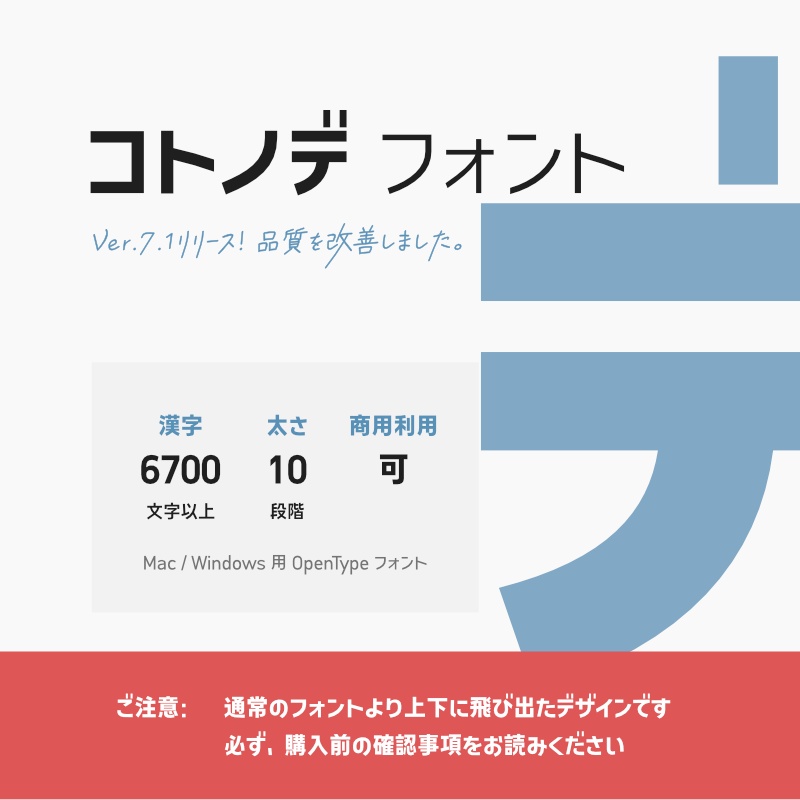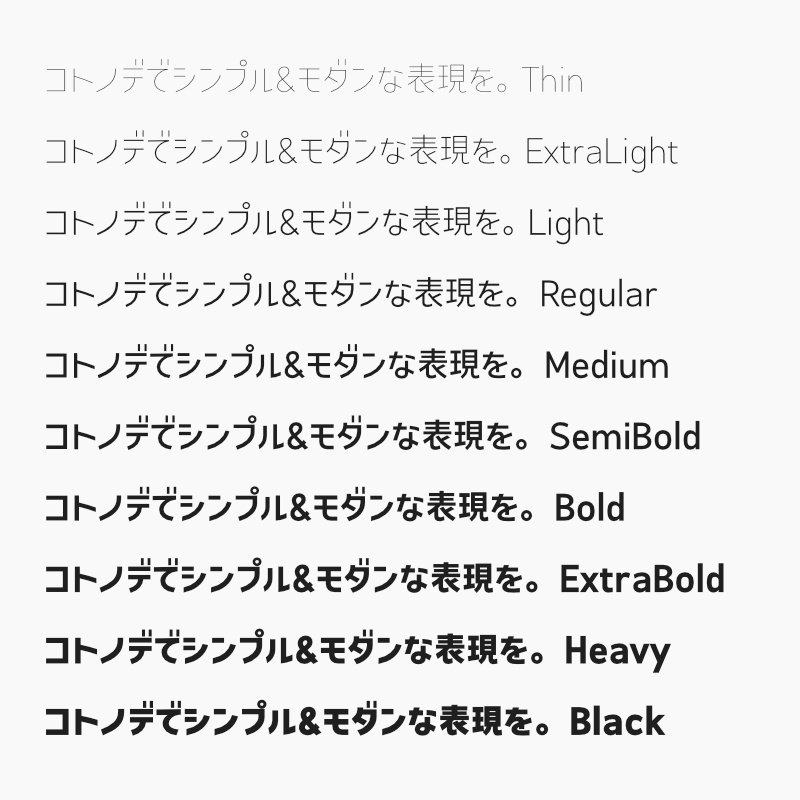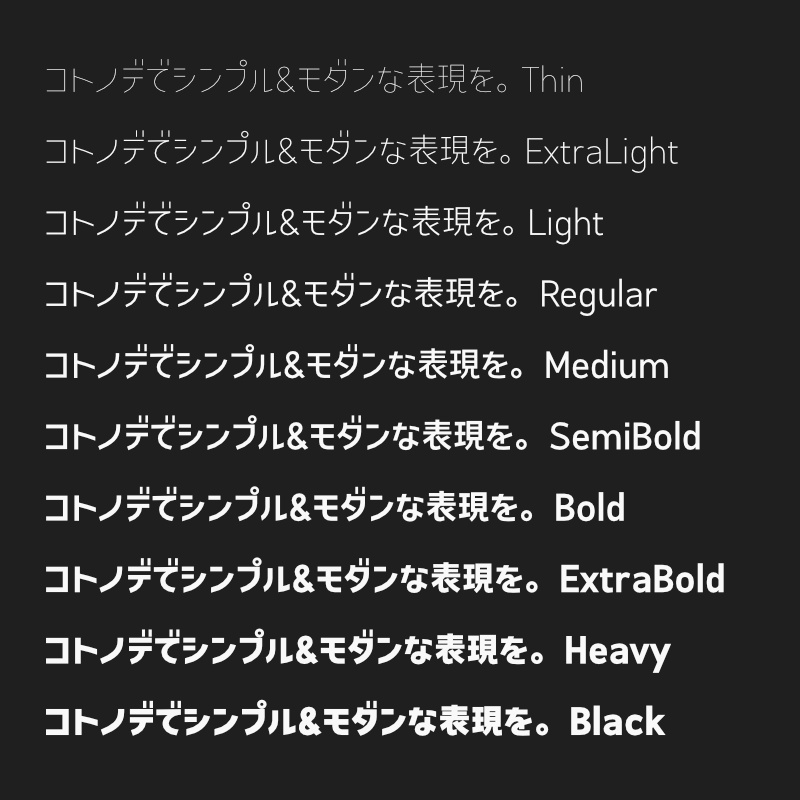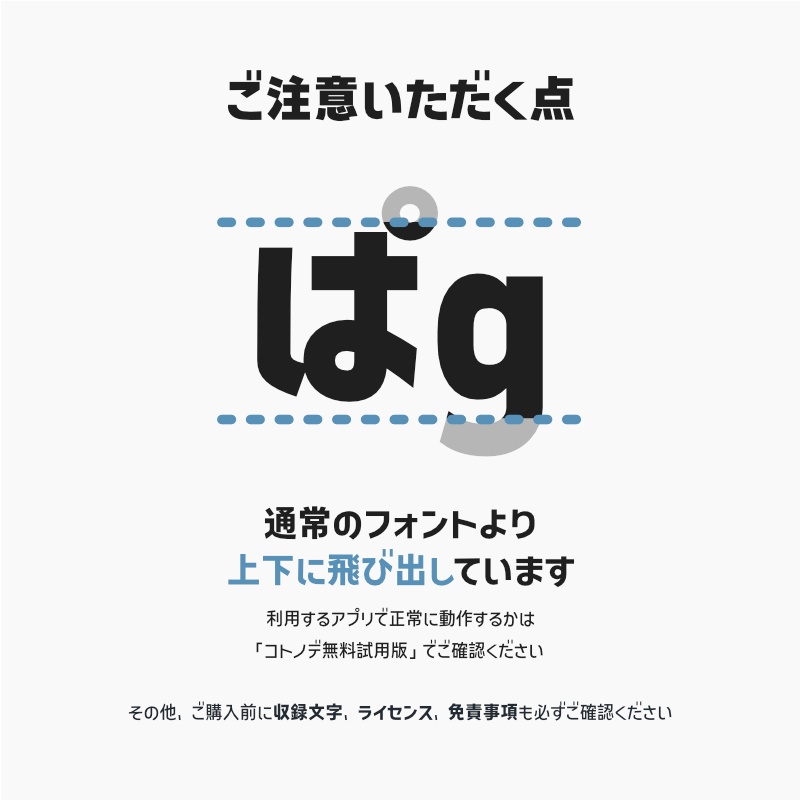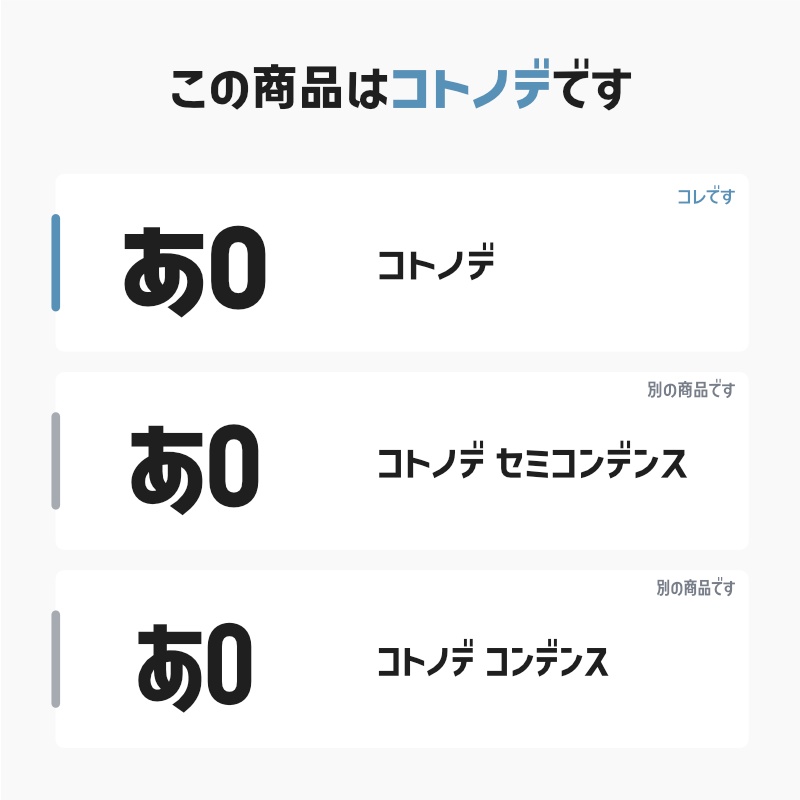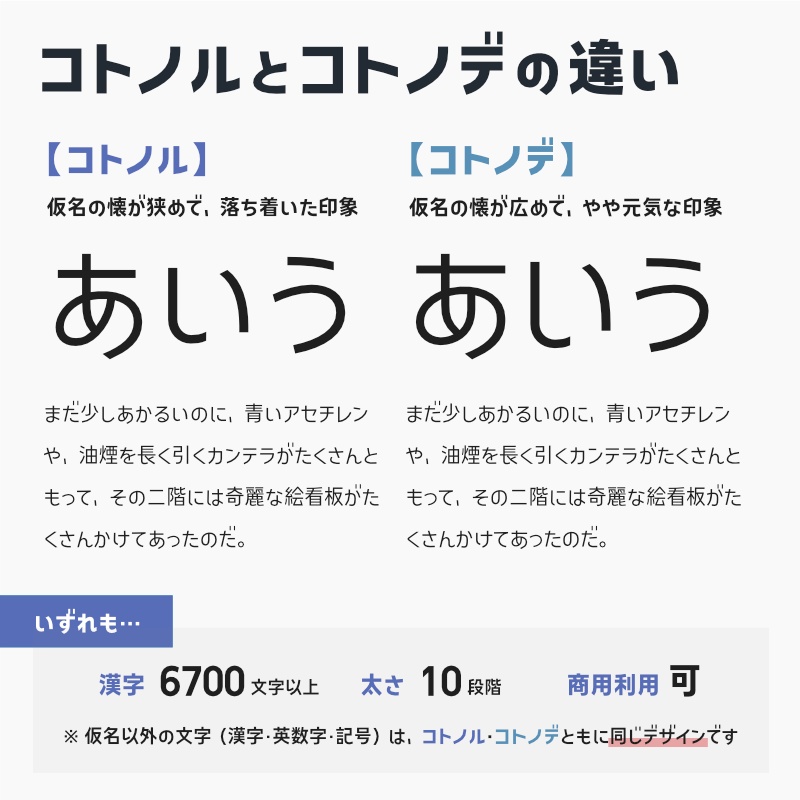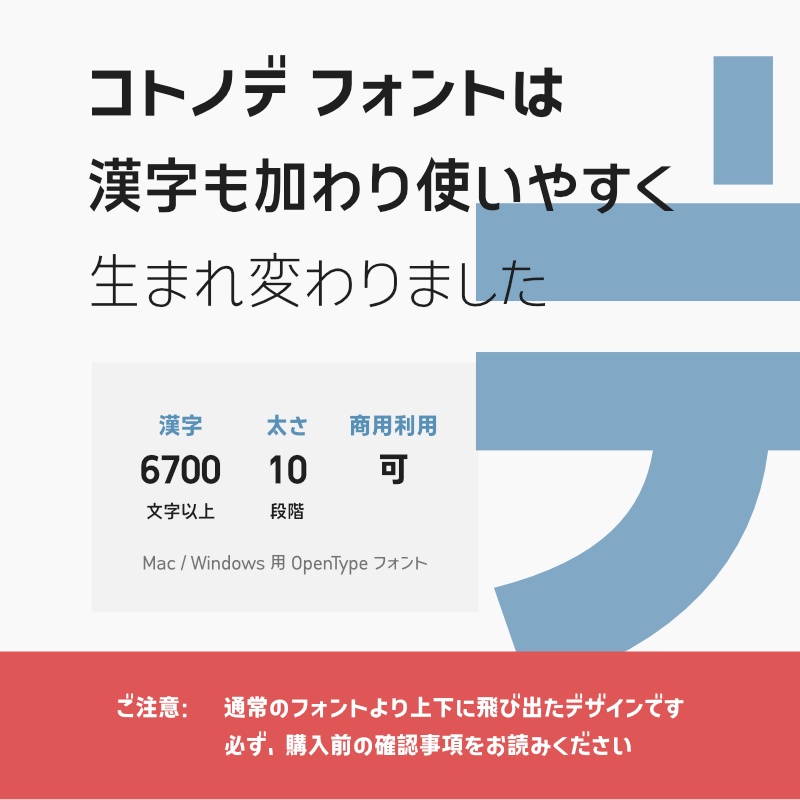
「コトノデ」フォント(漢字あり) ~シンプルで明るい雰囲気のゴシック体~
・通常のフォントよりも上下にはみ出たデザインです。ご利用のアプリによっては上下が見切れることがあります。ご購入前に、「コトノデ無料試用版(※)」で確認可能です。 ・漢字は6,700文字以上収録しており、常用漢字・JIS第一水準漢字・JIS第二水準漢字をカバーしています。収録文字は公式の紹介ページをご確認ください。 ・公式の紹介ページの利用規約・免責事項を必ず確認してください(商用利用可・再配布禁止)。 【公式の紹介ページ】 https://kotonohaworks.com/kotonode.html (※コトノデ無料試用版) https://dkf.booth.pm/items/2727320(無料試用版に漢字は含まれていません。) ※購入済み商品の最新版は、「購入履歴」「ライブラリ」ページからダウンロードできます。
2023/03/17 ver.1 リリース。漢字3,522文字収録(常用漢字・JIS第一水準漢字カバー。第二水準漢字は530文字のみ) 2023/04/24 ver.1.220 リリース。漢字4,259文字収録(常用漢字・JIS第一水準漢字カバー。第二水準漢字は1,205文字のみ) 2023/07/19 ver.1.520 リリース。漢字6,781文字収録(常用漢字・JIS第一水準漢字・第二水準漢字カバー) 2023/08/10 ver.1.540 リリース。ひらがなの懐の広さを調整しました。また、全体的な調整も行いました。 2023/08/22 ver.1.610 リリース。仮名のデザインのクセを軽減し、よりあらゆる場面で利用しやすくなるよう改善しました。 2023/09/05 ver.1.730 リリース。文字組がより自然になるよう、いくつかの漢字のデザインを微調整しました。 2023/09/27 ver.1.745 リリース。一部環境において、出力したPDFで文字化けが発生するバグを修正しました。 2023/10/02 ver.1.800 リリース。一部の漢字グリフの特定の中間ウェイトにおいて、文字の一部が塗り潰されるなどの不具合を修正しました。また、小文字のローマ数字などの記号を追加しました。 2023/10/10 ver.1.825 リリース。アルファベットのデザインのバランスを改善しました。 2023/10/27 ver.1.845 リリース。アルファベットのデザインの整合性を改善しました。 2023/12/08 ver.2.000 リリース。記号のデザインバランスの修正・整合性の改善を行ないました。また、一部漢字デザインを改善しました。 2024/01/17 ver.2.020 リリース。一部漢字のデザインを調整しました。 2024/02/27 ver.2.040 リリース。Regular~SemiBoldの3ウェイトをより自然に見えるよう微調整しました。 2024/04/22 ver.2.700 リリース。「粂」の文字を修正しました。漢字約4,000字をより自然なデザインに見えるよう改善しました。 2024/05/16 ver.3.000 リリース。残りの漢字もより自然なデザインに見えるよう改善しました。 2024/05/28 ver.3.100 リリース。仮名・漢字の字間広げ、一般的な文字組と同程度に改善しました。フォント名の末尾に「Kw-N」を付与しました。 2024/07/25 ver.3.230 リリース。いくつかの文字のデザインを微調整しました。 2024/08/05 ver.3.400 リリース。いくつかの文字のデザインを微調整しました。 2024/08/15 ver.3.410 リリース。「鍛」の文字を修正しました。 2024/08/30 ver.3.412 リリース。いくつかの文字のデザインを微調整しました。 2025/01/14 ver.3.600 リリース。一部の文字の表示崩れを修正しました。 2025/03/25 ver.4.105 リリース。濁点の位置を微調整しました。いくつかの文字のデザインを微調整しました。 2025/09/08 ver.4.106 リリース。「以」「似」などを画数に忠実なデザインに変更しました。 2026/01/30 ver.5.001 リリース。「篝」をJIS2004字形に変更しました。 2026/08/31 ver.7.108 リリース。「ð」「冕」2文字の誤字を修正しました。主に英数字において、曲線と直線の遷移をなめらかにしました。いくつかの文字(主に漢字)において、小さな凹みや欠片の除去を行いました。仮名文字の字間調整を行いました。その他いくつかの修正を加えました。その他、ウェイト差におけるデザインの一貫性向上、各ウェイトの太さの微調整(それに伴う横幅調整)なども行いました。 【ver.7.108へのアップデート時のご注意】文字幅変更を伴うアップデートです。旧バージョンのフォントファイルはバックアップを取り、フォントを更新した際は、成果物のレイアウトに崩れがないか必ずご確認ください。 【ver.7.108 更新内容(見本付き)】https://kotonohaworks.com/shiryou-pdf/update_kotonode-n-sc-c_ver7-1.pdf